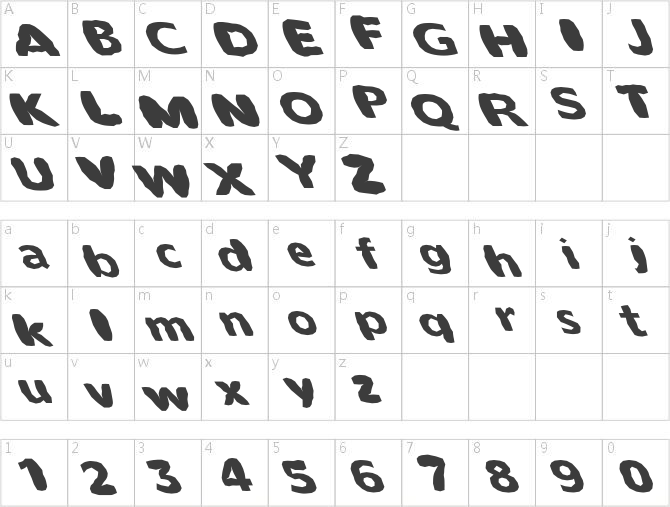
FZ BASIC 55 MANGLED LEFTY
FZ BASIC 55 MANGLED LEFTY介紹
FZ BASIC 55 MANGLED LEFTY字體字庫是一款讓人賞心悅目、百看不厭的英文字體,適合各類廣告和產品包裝設計應用,字體大小0.07MB,格式為ttf字體,上傳用戶是Elieen,作者/版權方為未知
FZ BASIC 55 MANGLED LEFTY效果圖